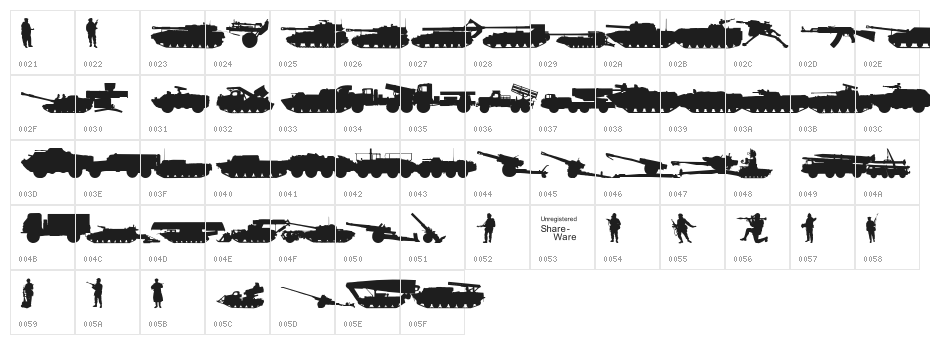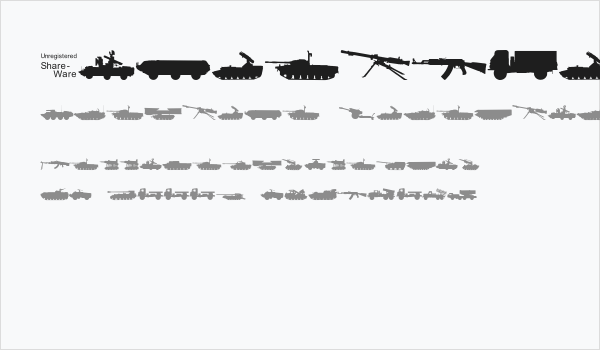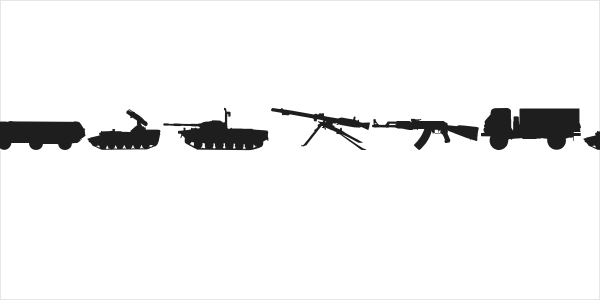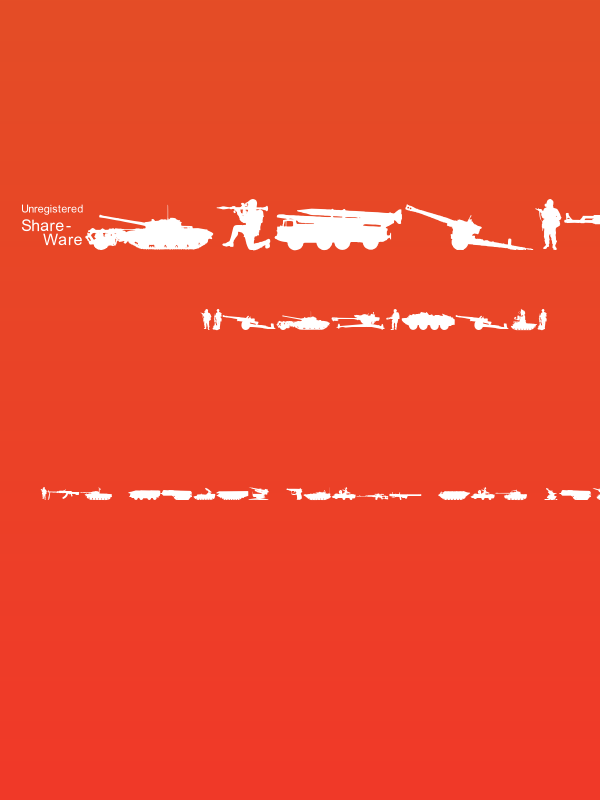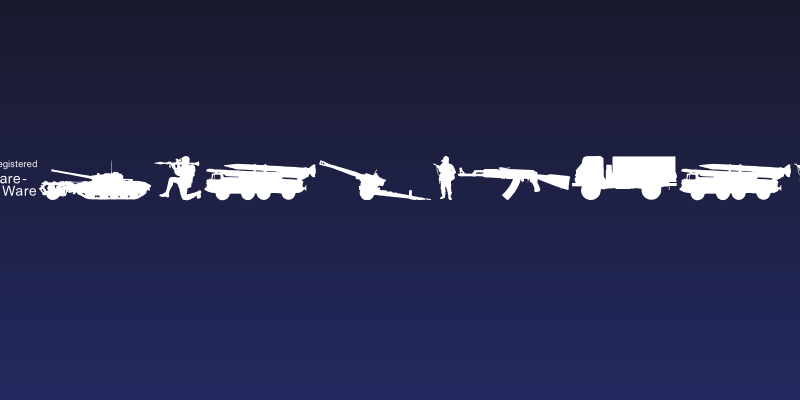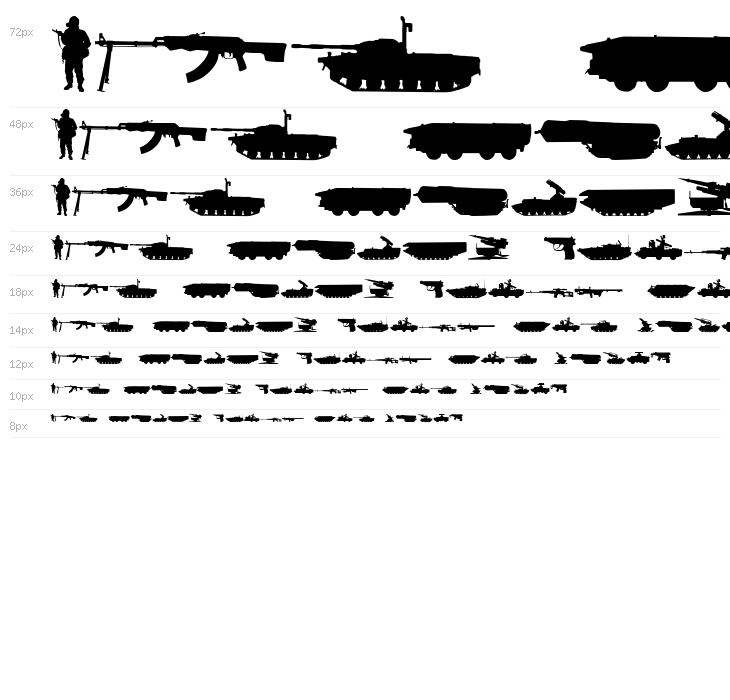
Soviet-Kit Font
| Catégories | Dingbats |
| Style général | Decorative, Thematic, Military |
| Cas d'utilisation | Headlines, Logos, Themed graphics, Posters |
| Projets proposés | Posters, historical presentations, themed event materials, video game titles, educational resources, military-themed designs. |